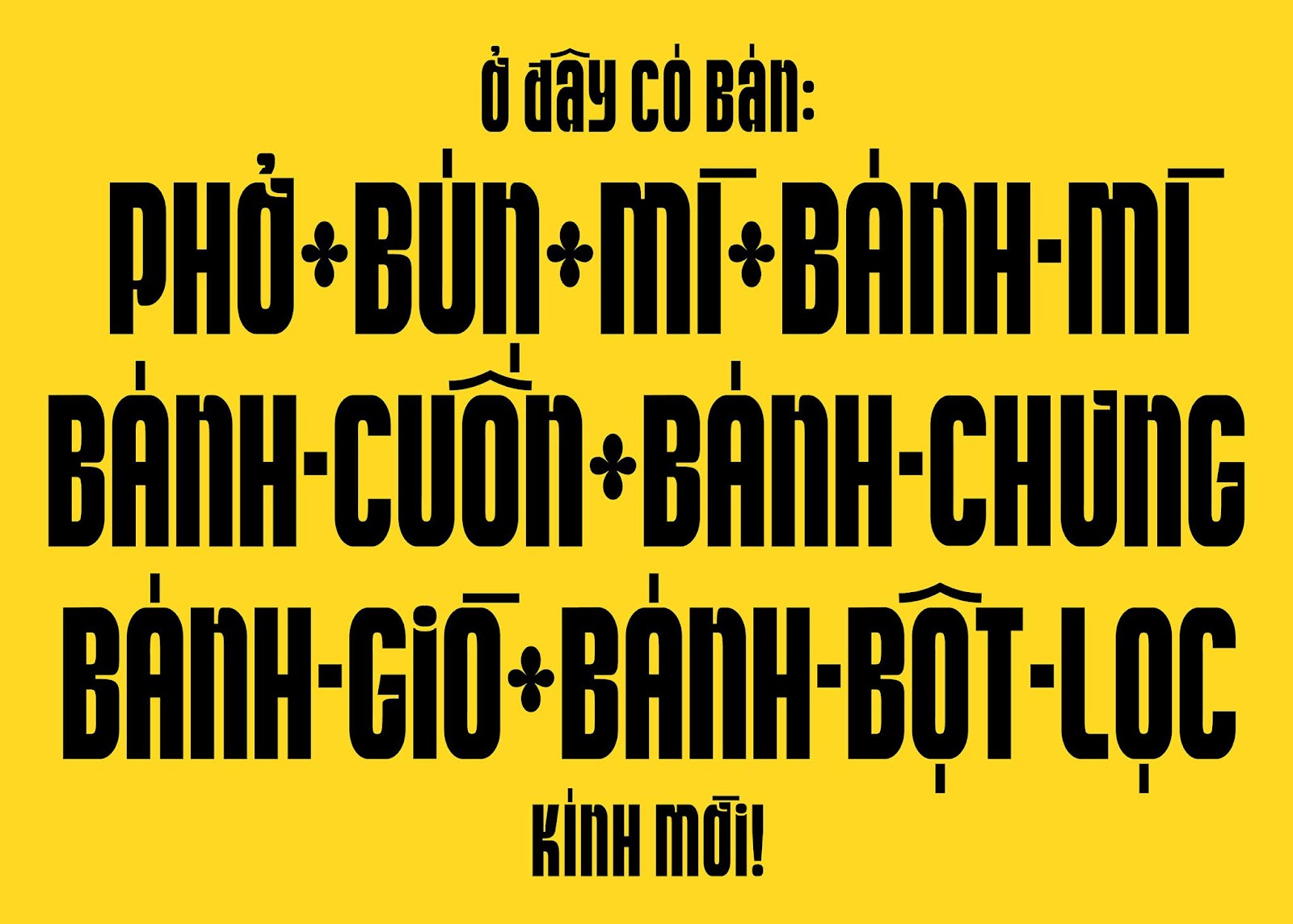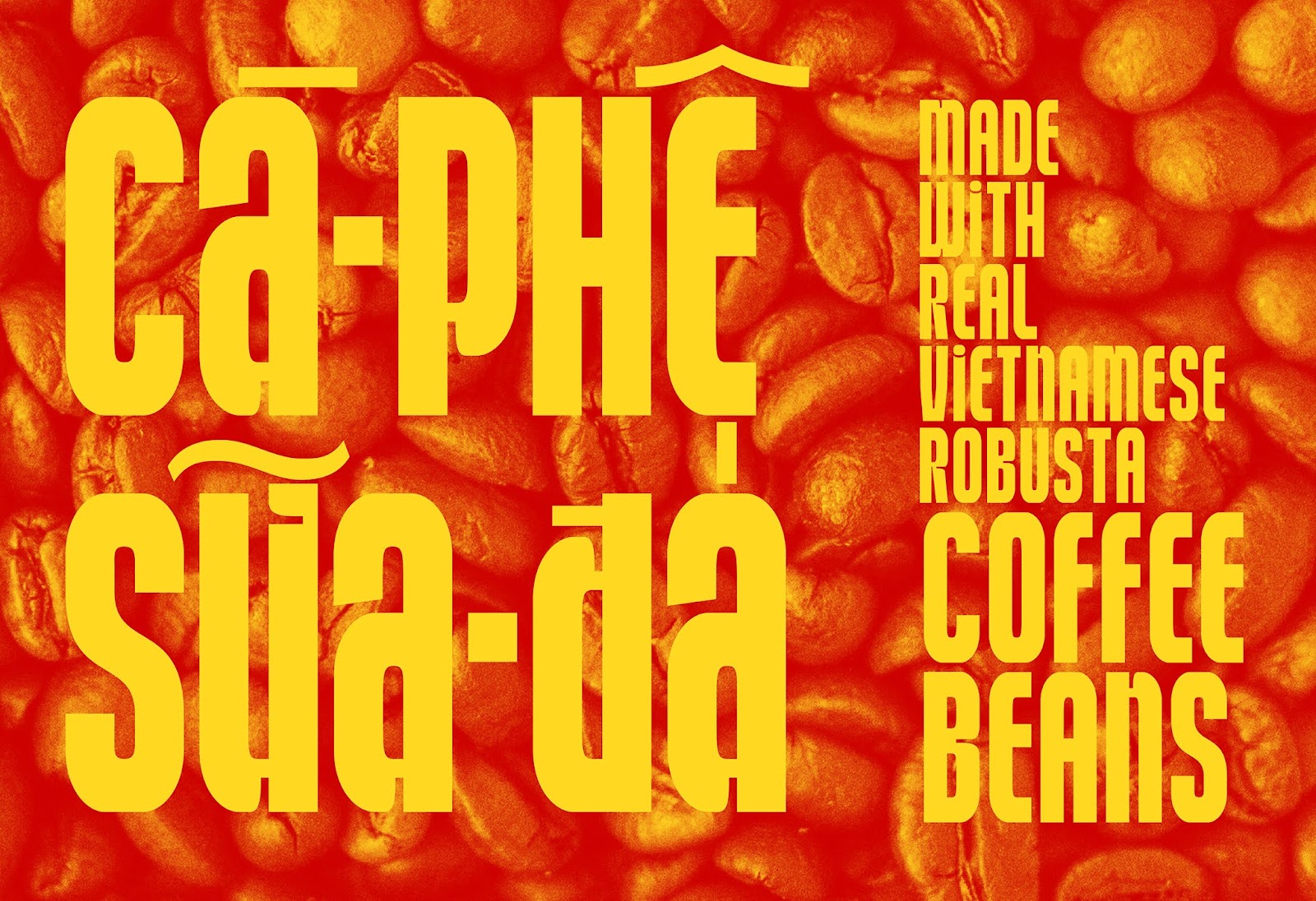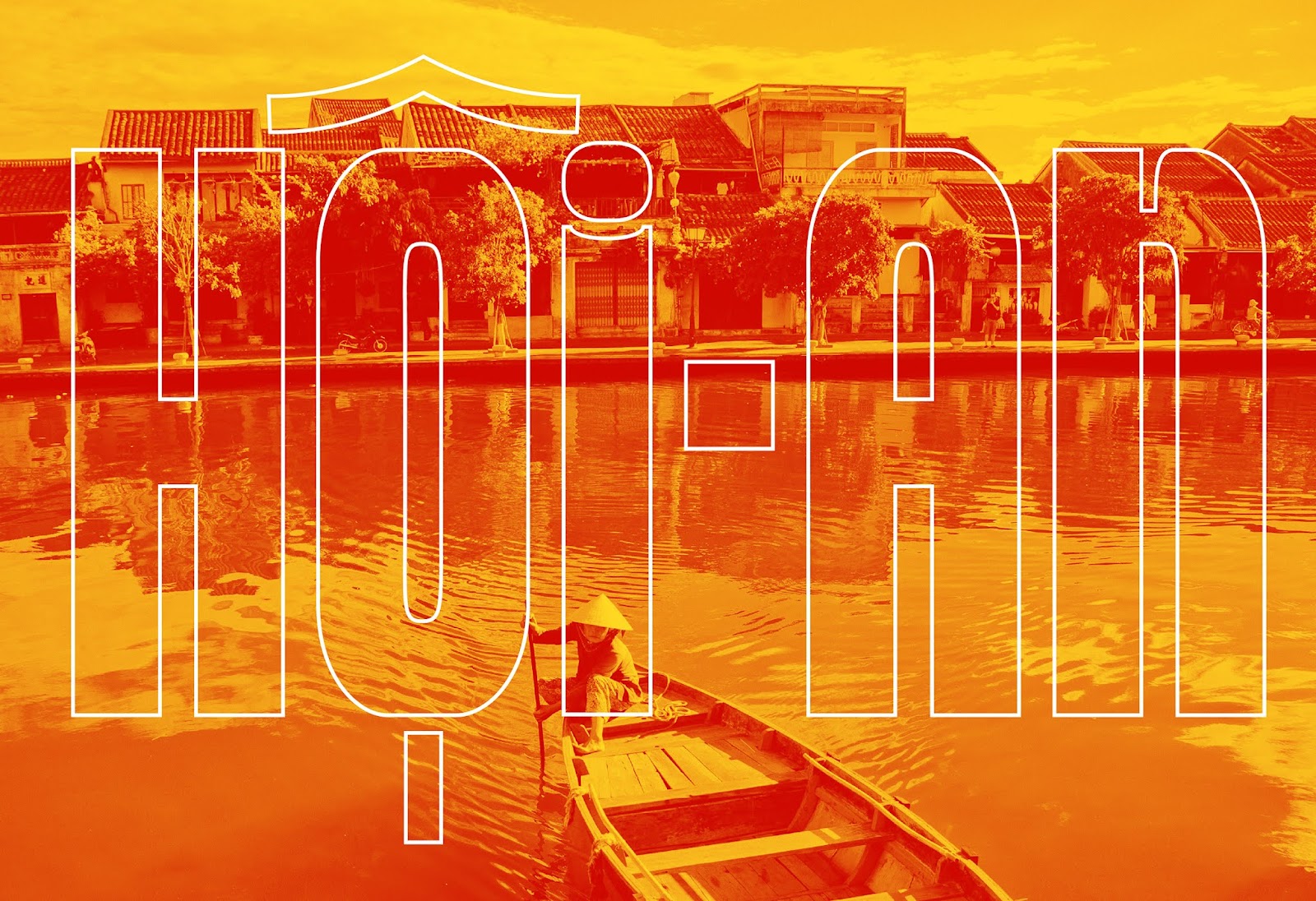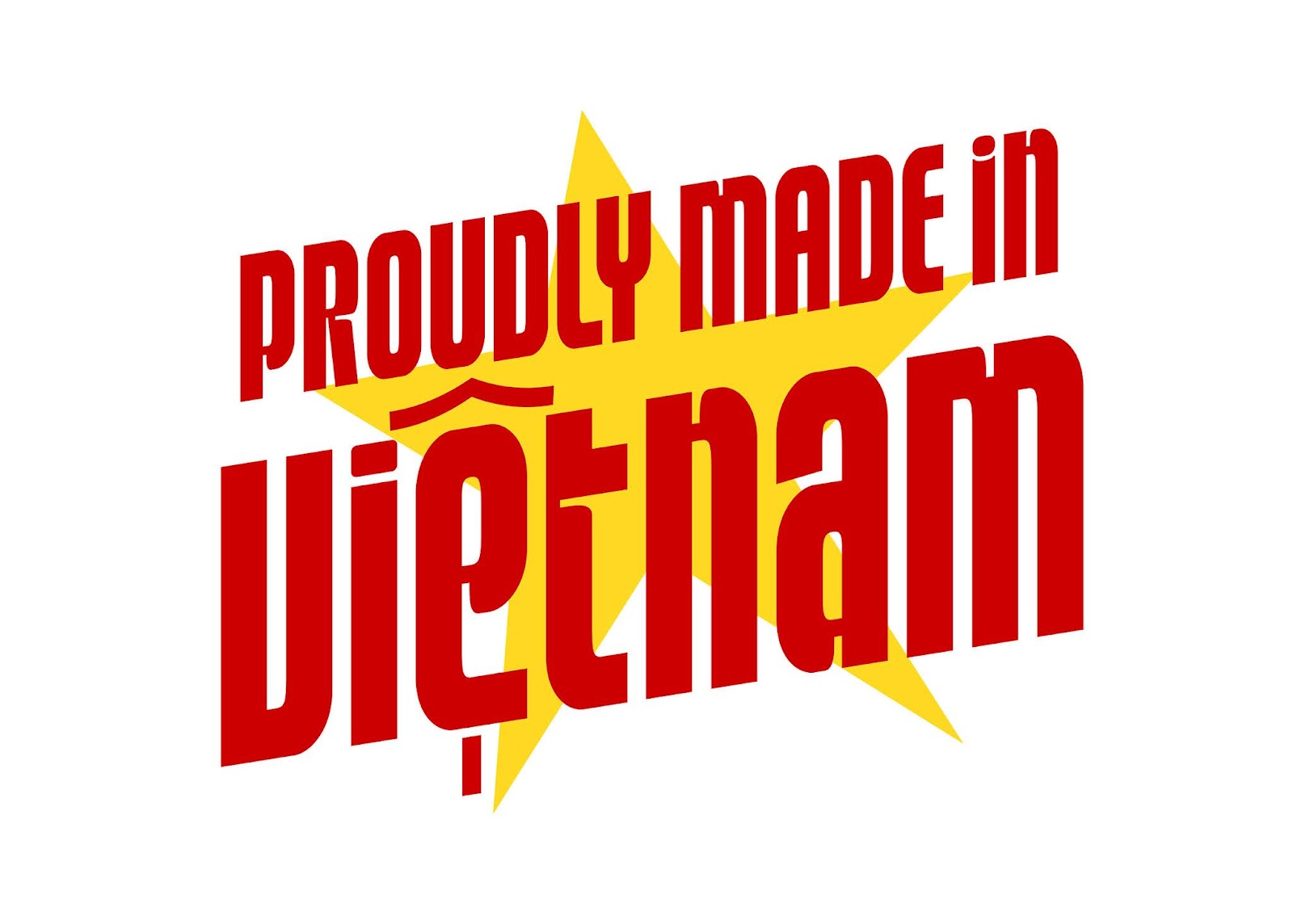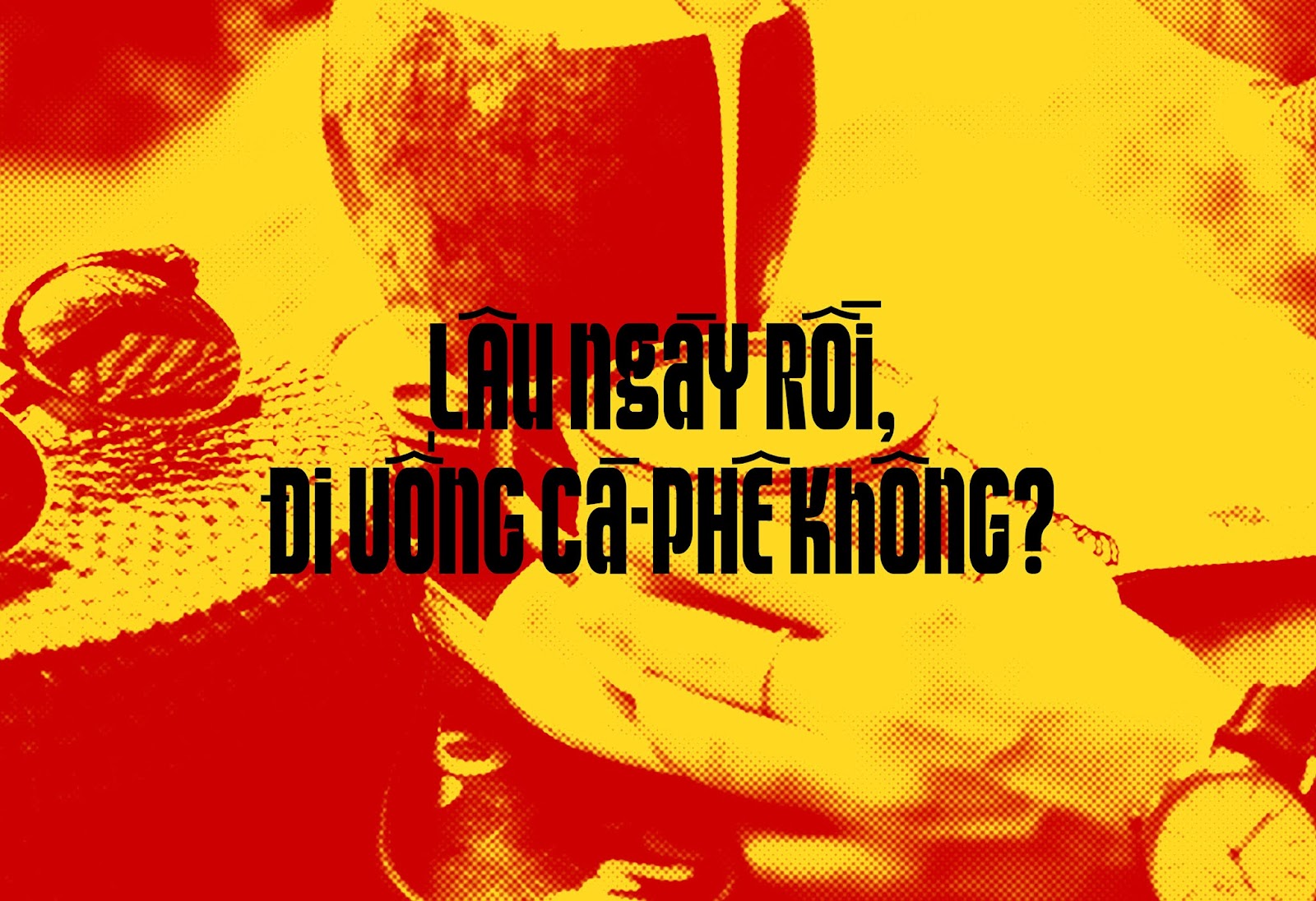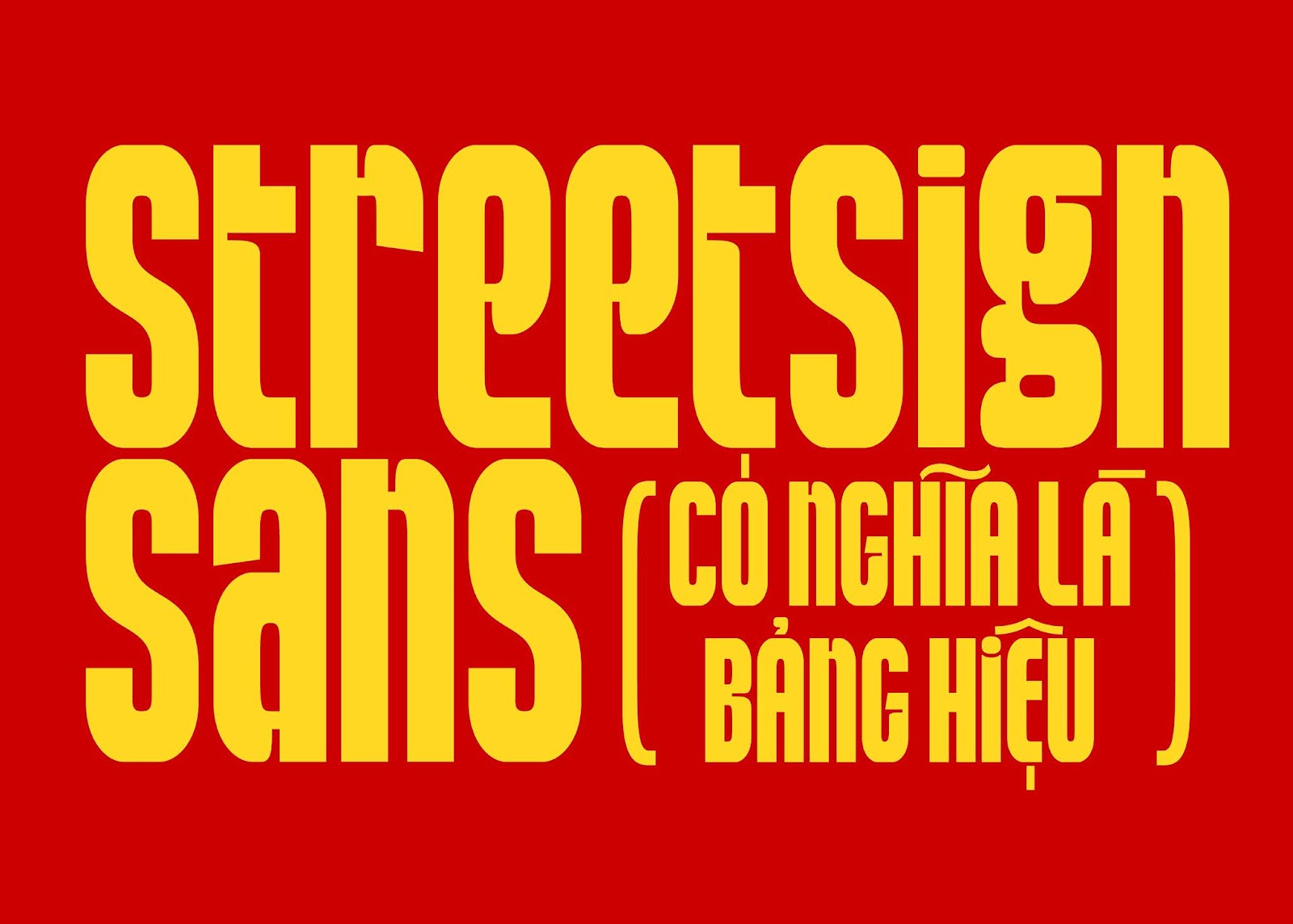
Font StreetSign Sans – Font xưa cũ cực đẹp
StreetSign Sans là một font chữ cực đẹp được tạo bởi người Việt đó là bạn Harry Dinh, một font chữ xưa cũ, cổ điển rất ấn tượng, phù hợp cho các thiết kế với sự hoài cổ, sang trọng và lãng mạn, phong cách của kỉ niệm, của dấu ấn thời gian hoặc cho bất kỳ thiết kế nào.